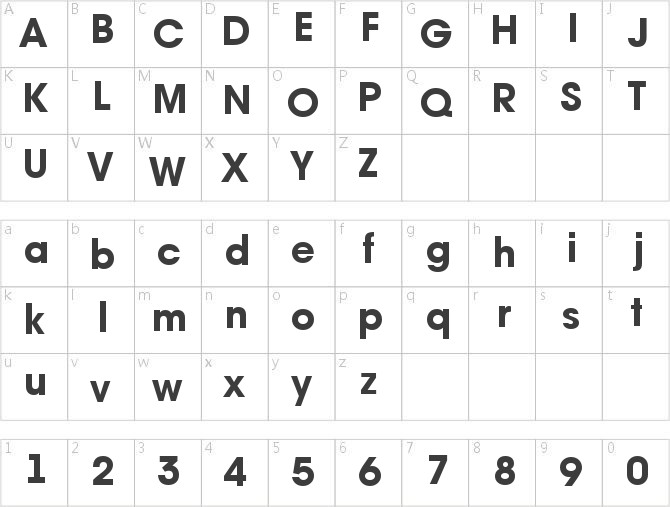
a_AvanteBs-ExtraBold 詳情頁(yè)
a_AvanteBs-ExtraBold字體字庫(kù)是一款讓人賞心悅目、百看不厭的英文字體,適合各類廣告和產(chǎn)品包裝設(shè)計(jì)應(yīng)用,字體大小0.04MB,格式為ttf字體,上傳用戶是曉語(yǔ)無(wú)聲,作者/版權(quán)方為未知